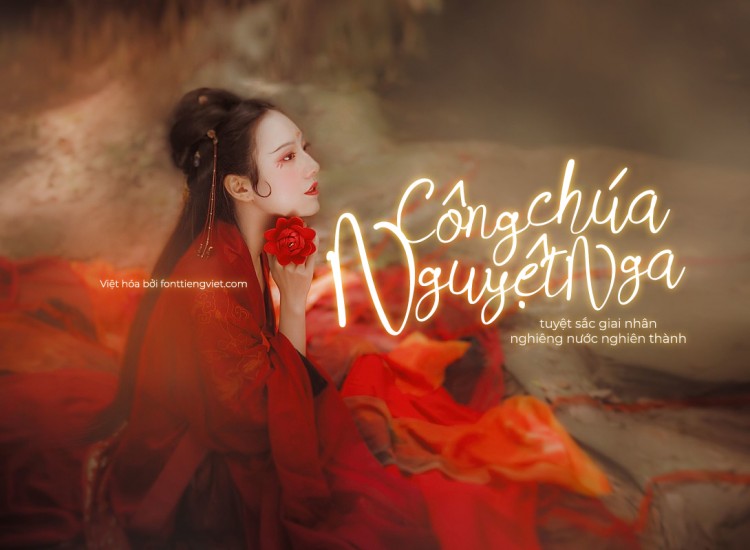
Font việt hóa 1FTV Gisellina phong cách thư pháp – Nghệ thuật chữ viết tinh tế cho thiết kế của bạn
Giới thiệu về Font việt hóa 1FTV Gisellina phong cách thư pháp
Trong thế giới đồ họa hiện đại, việc tìm kiếm một bộ Font Chữ vừa mang nét truyền thống vừa mang tính ứng dụng cao là điều không hề dễ dàng. Font việt hóa 1FTV Gisellina phong cách thư pháp xuất hiện như một giải pháp hoàn hảo dành cho những ai yêu thích sự mềm mại và uyển chuyển. Đây là bộ font được lấy cảm hứng từ những nét vẽ thủ công tỉ mỉ, giúp truyền tải cảm xúc chân thực vào từng khung hình. Với phiên bản đã được việt hóa chỉn chu, người dùng có thể thoải mái sáng tạo các nội dung tiếng Việt mà không lo lỗi font hay thiếu dấu.
Đặc điểm nổi bật của Font việt hóa 1FTV Gisellina phong cách thư pháp
Nét vẽ thanh mảnh và đầy tính nghệ thuật
Đặc trưng lớn nhất của Font việt hóa 1FTV Gisellina phong cách thư pháp chính là những đường lượn sóng tinh tế và các nét thanh nét đậm đan xen hài hòa. Phong cách thư pháp hiện đại này tạo nên vẻ đẹp sang trọng, phù hợp cho các mục đích trang trí khác nhau. Các ký tự được thiết kế với độ nảy tự nhiên, mô phỏng lại cách đưa bút của những nghệ nhân viết chữ nghệ thuật chuyên nghiệp.
Ứng dụng đa dạng trong nhiều lĩnh vực thiết kế
Bạn có thể sử dụng bộ font này cho nhiều dự án khác nhau như thiết kế thiệp cưới, bìa sách, menu nhà hàng hay các tiêu đề blog cá nhân. Nhờ sự linh hoạt, font chữ giúp sản phẩm trở nên nổi bật và thu hút thị giác người xem ngay từ cái nhìn đầu tiên. Đặc biệt, đối với các bạn học sinh và sinh viên, đây là công cụ đắc lực để trang trí các bài thuyết trình thêm phần ấn tượng và sáng tạo.